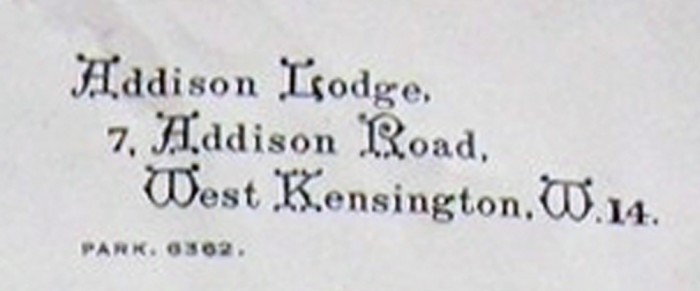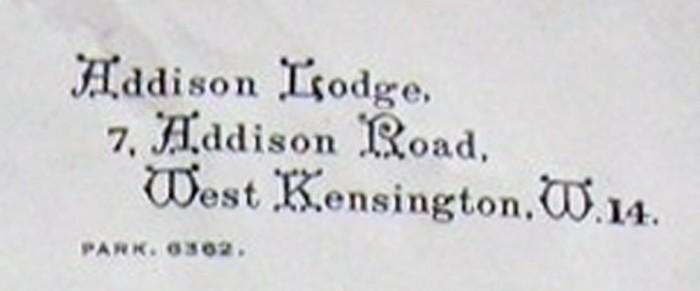
Briefkopf Violet Van der Elst
die englische Todesstrafengegnerin Violet Van der Elst schrieb 1943 in London an den Innenminister einen Brief, dessen gedruckter Briefkopf mich wegen seiner sehr ungewöhnlichen Schrift interessiert. Die angehängte Datei ist ein Ausschnitt aus einem Foto, das jemand im Brit. Nationalarchiv von dem betreffenden Aktenstück gemacht hat.
Was für eine Schrift ist das, und gibt's die (oder eine sehr ähnliche) in digitalisierter Form irgendwo?